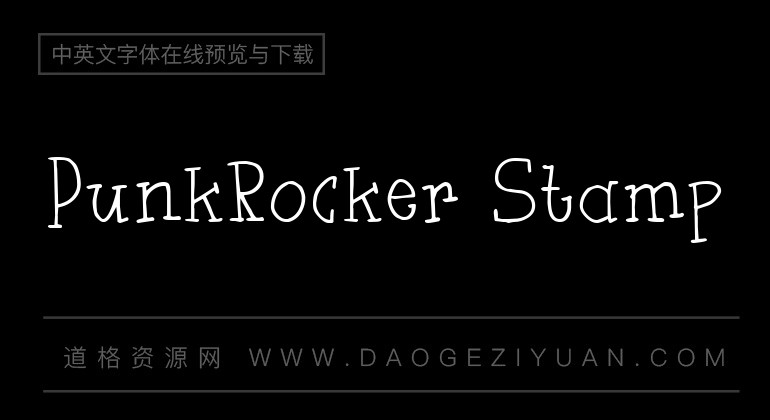
PunkRocker Stamp
? PunkRocker Stamp 字体是一款具有独特复古风格的英文字体,它的特点是字母间距较大,字体外观有一定的倾斜,有着强烈的摇滚气息,可以给设计师带来丰富的创意灵感。它可以用于各种品牌标识、海报、T恤、电影海报、书籍封面等设计之中,也可以与多种其他字体混合使用,带来更多的设计灵感。
PunkRocker Stamp是一款非常不错的手写艺术字体,具有很好的视觉感,适合于文化类的宣传设计、商业类品牌的广告和产品包装设计以及个性化文字排版等较多场景。